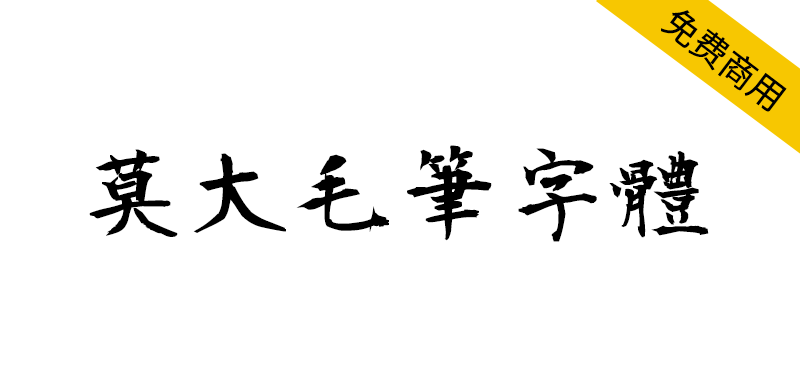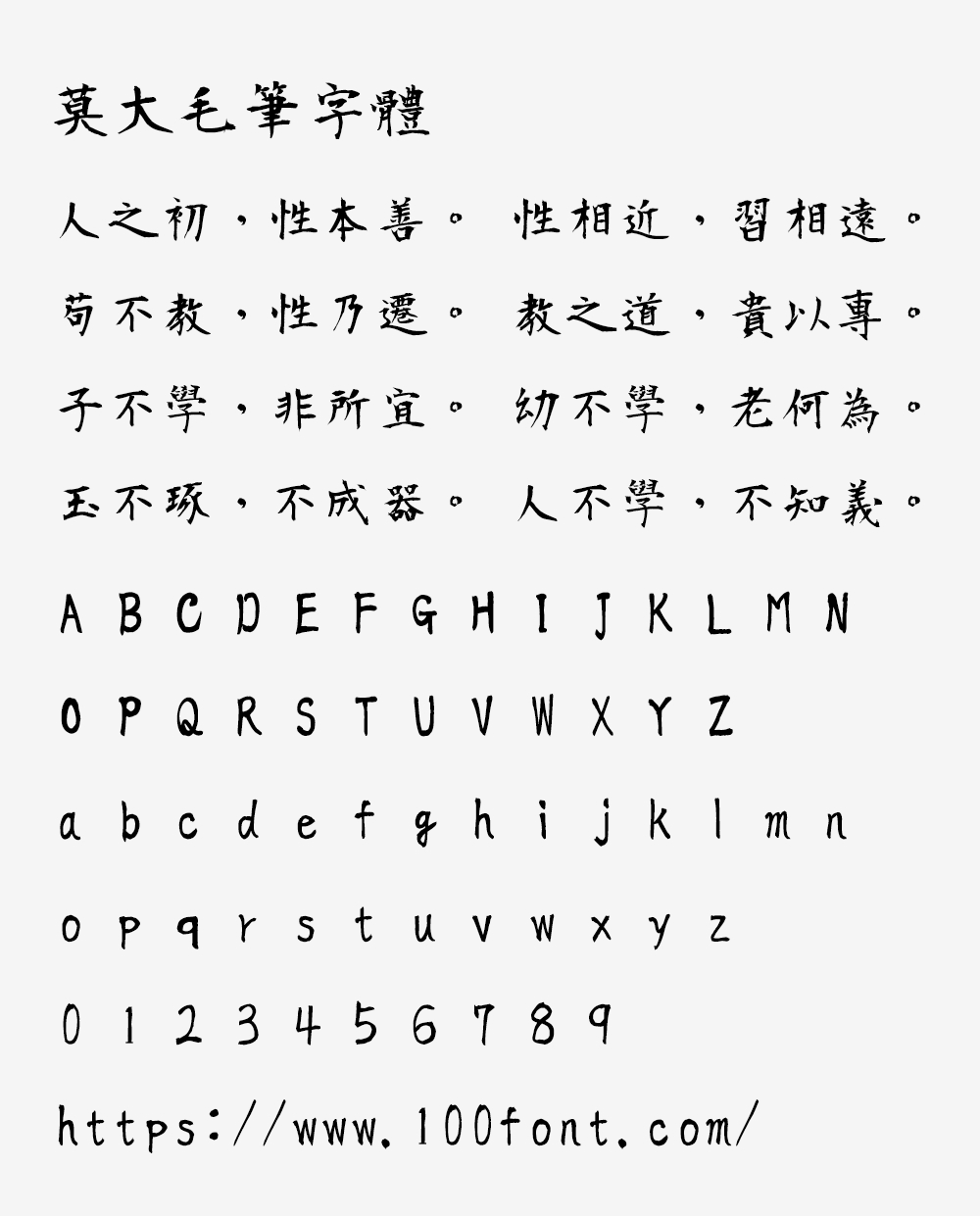
莫大毛笔字体是基于衡山毛笔字体的开放原始码中文字型。衡山毛笔字体是来自于日本书法家青柳衡山,修改前文字+符号数约:13,000字,修改后文字+符号数:24,896字,增加11,281字符。可以免费商用,欢迎大家自由应用、自由优化、自由改作!
字体特色:弥补繁体中文常用字缺字缺憾,调整为5种字重,清除衡山毛笔字体里空白的文字,标点符号位置调整为台湾常见的置中用法,增加部分台湾口语、粤语字、闽南语和客语中文字。